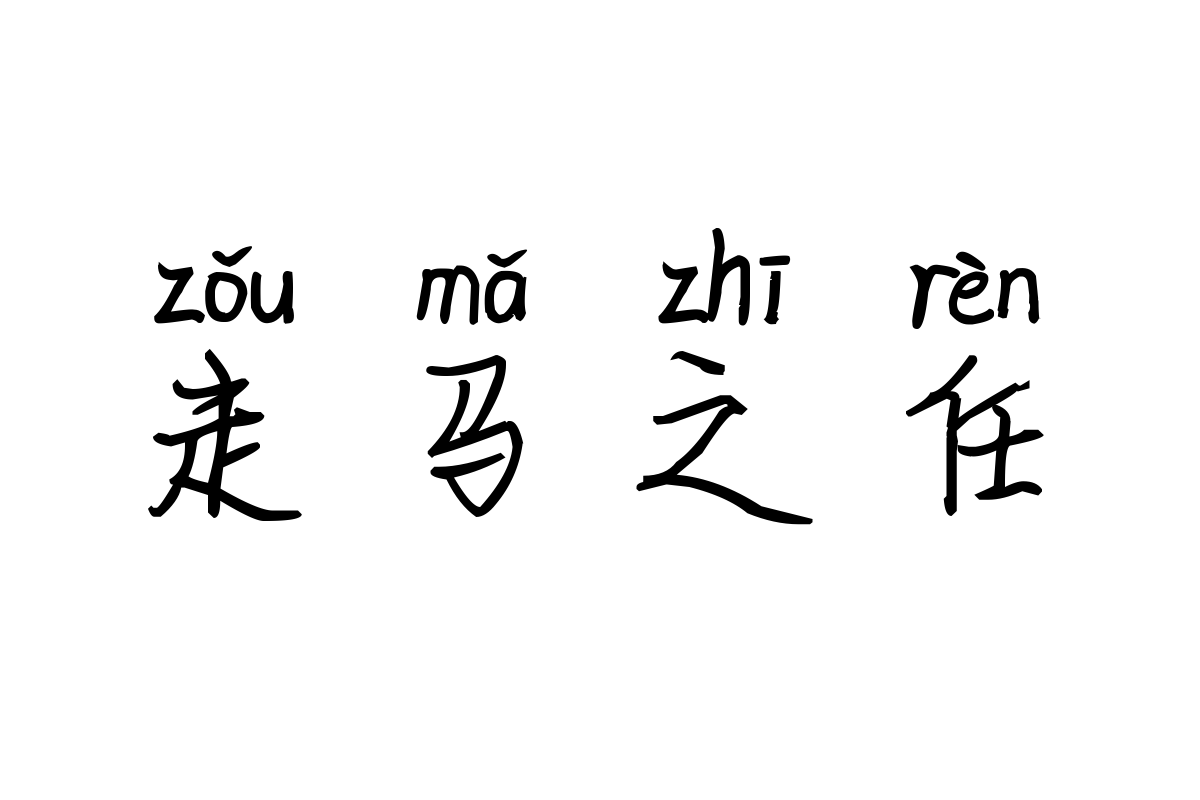
米开红颜醉拼音体是一款具有独特风格的中文字体,它采用了传统的书法艺术元素,结合现代设计手法,创造出一种既古典又时尚的字体风格。这款字体的特点如下:
1. 字形结构:米开红颜醉拼音体采用了较为复杂的字形结构,笔画粗细不一,既有传统的楷书韵味,又不失现代感。这种独特的字形结构使得字体在视觉上具有很强的冲击力和辨识度。
2. 字体风格:这款字体融合了传统书法的线条美感与现代设计的简洁风格,给人一种既优雅又现代的感觉。它的笔画流畅自然,既有力度又有柔美,适合用于各种文字设计场景。
3. 适用范围:米开红颜醉拼音体适用于需要突出个性和艺术气息的文字设计,如标题、正文、广告等。同时,由于其独特的字形结构,也适合用于一些创意性较强的项目,如插画、漫画等。
总之,米开红颜醉拼音体是一款极具个性和艺术气息的中文字体,它以其独特的字形结构和风格,为文字设计带来了新的可能。无论是用于个人项目还是商业项目,这款字体都能为您的作品增色添彩。